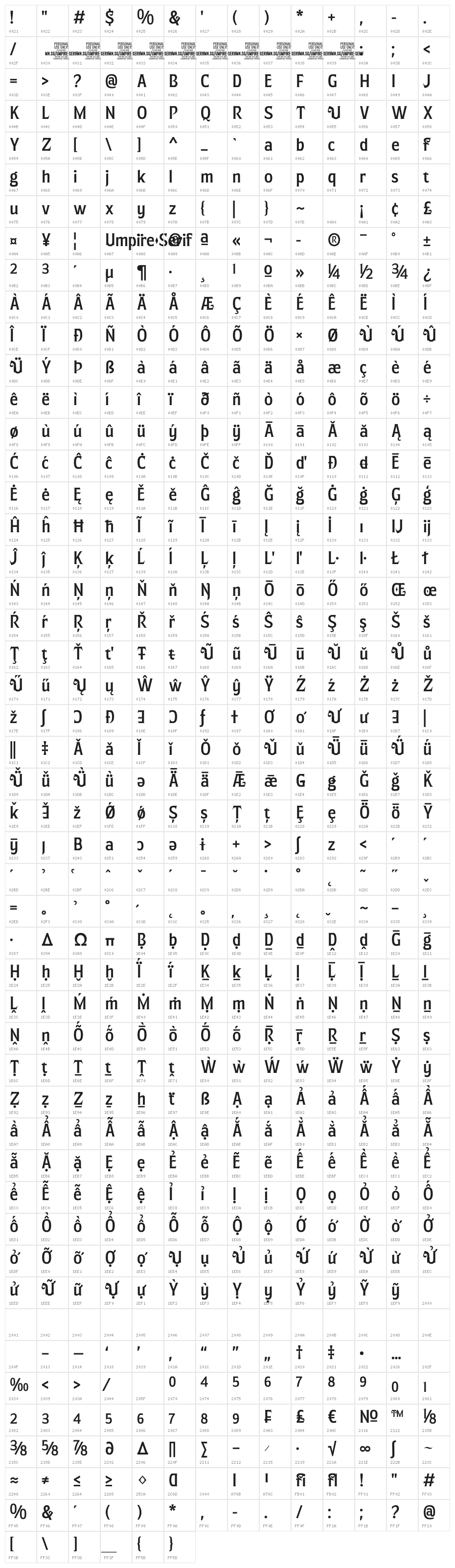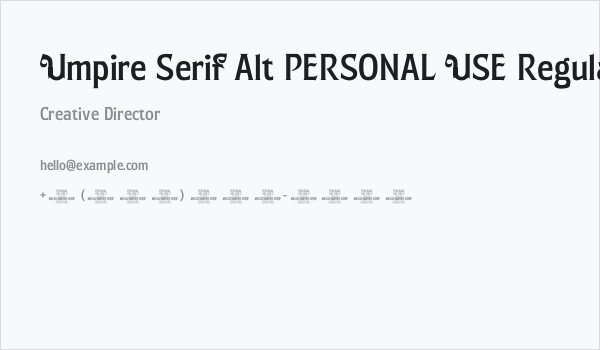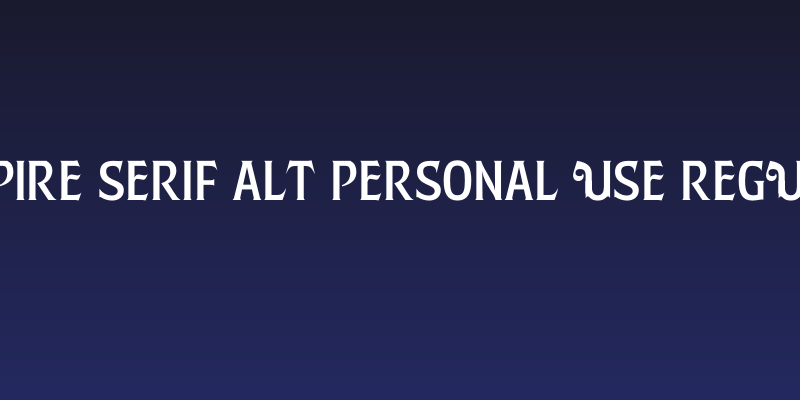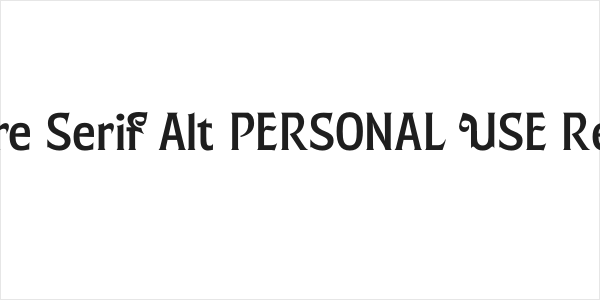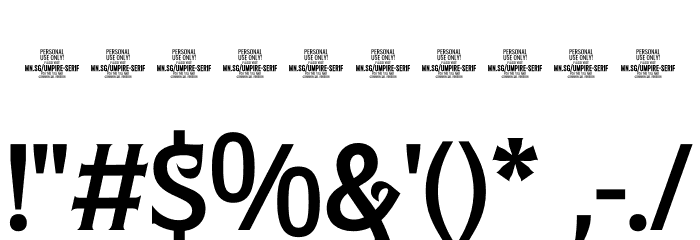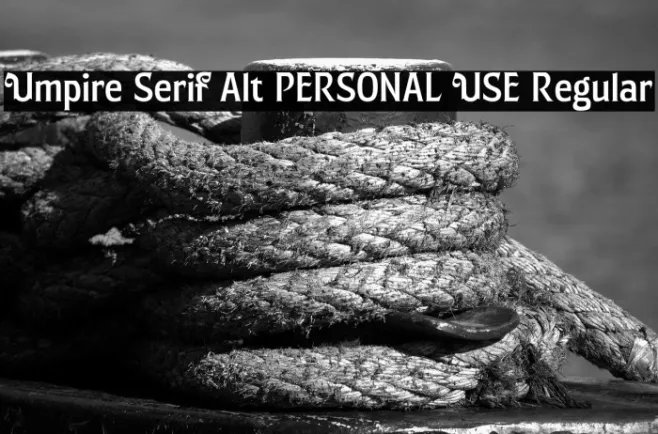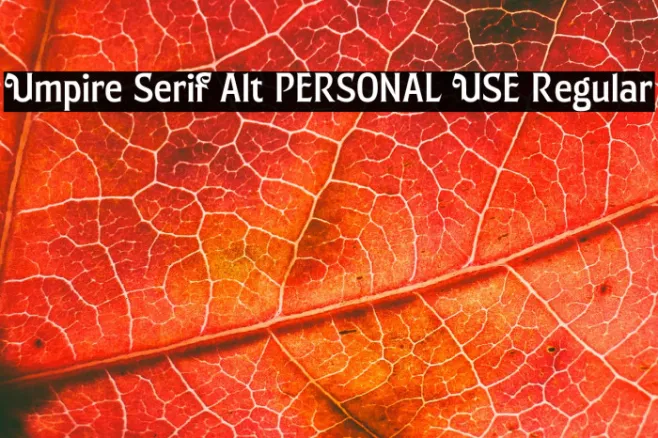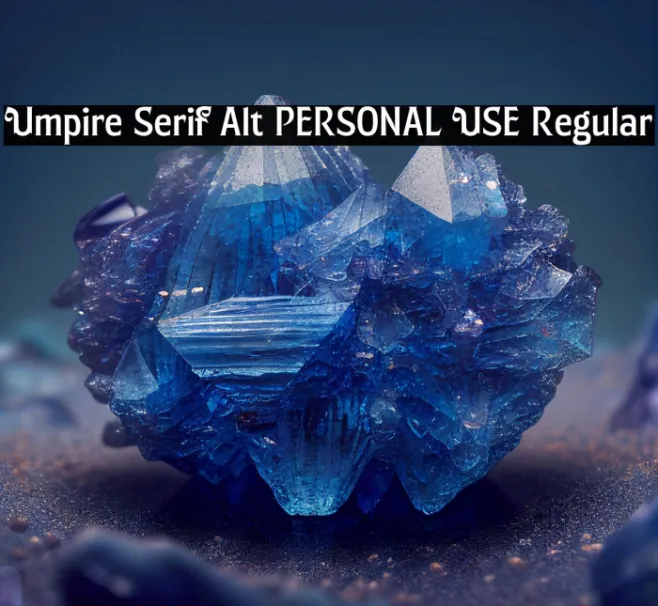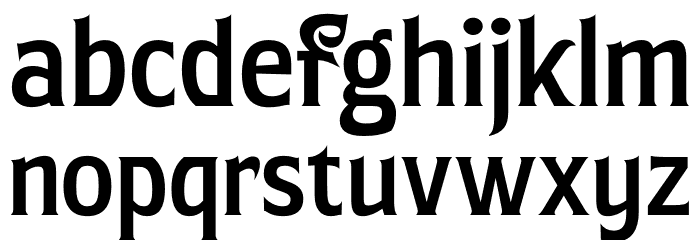
Umpire Serif Alt PERSONAL USE Regular Font
| Anwendungsfall | Headlines, Logos, Editorial Design |
| Vorgeschlagene Projekte | Ideal for branding, editorial design, and advertising where a modern yet classic look is desired. |